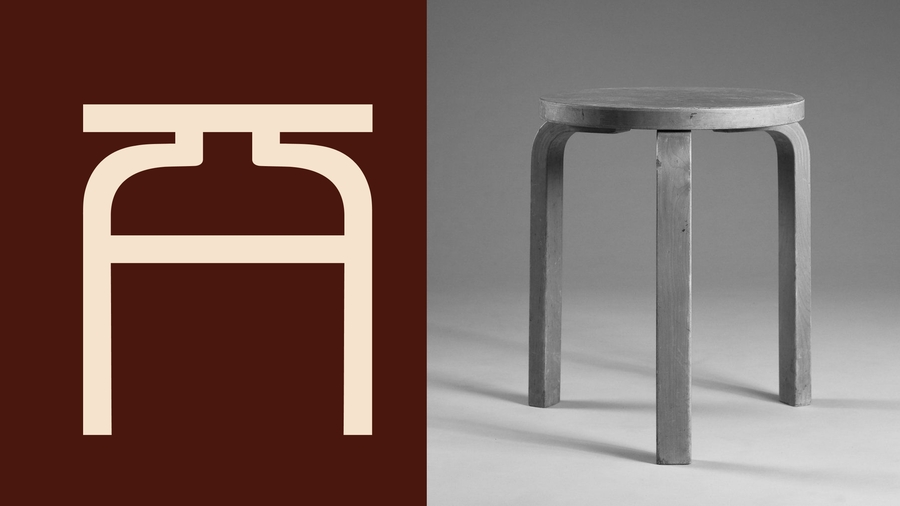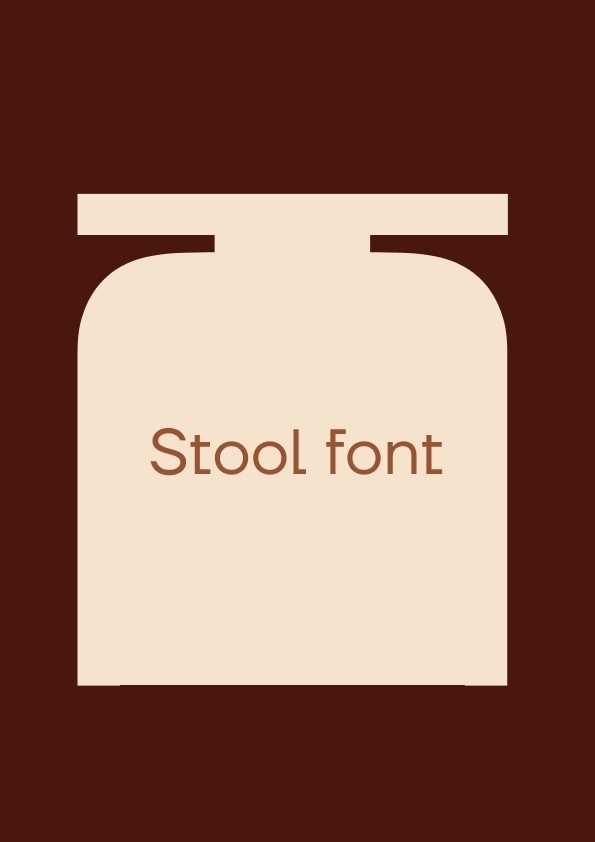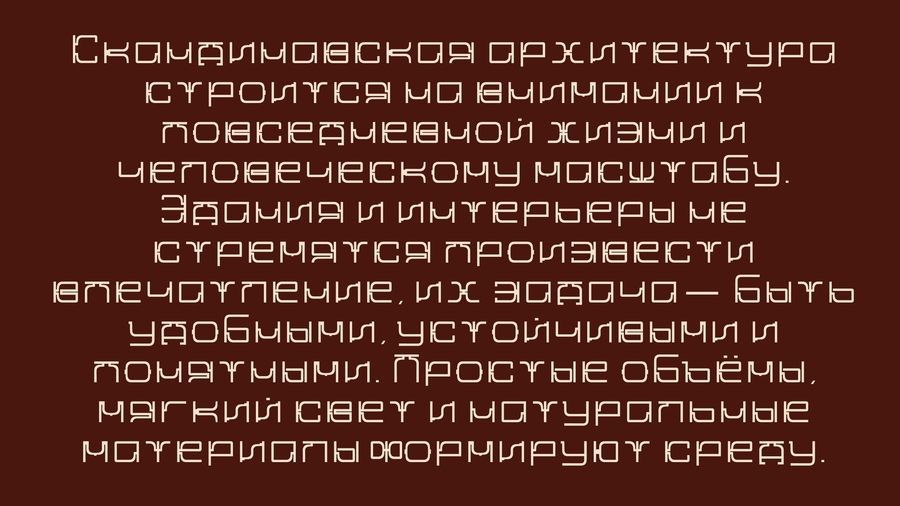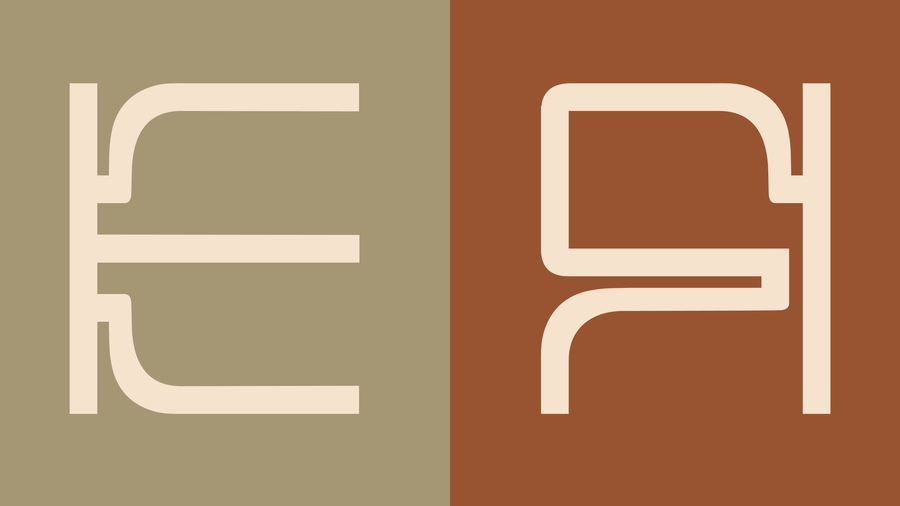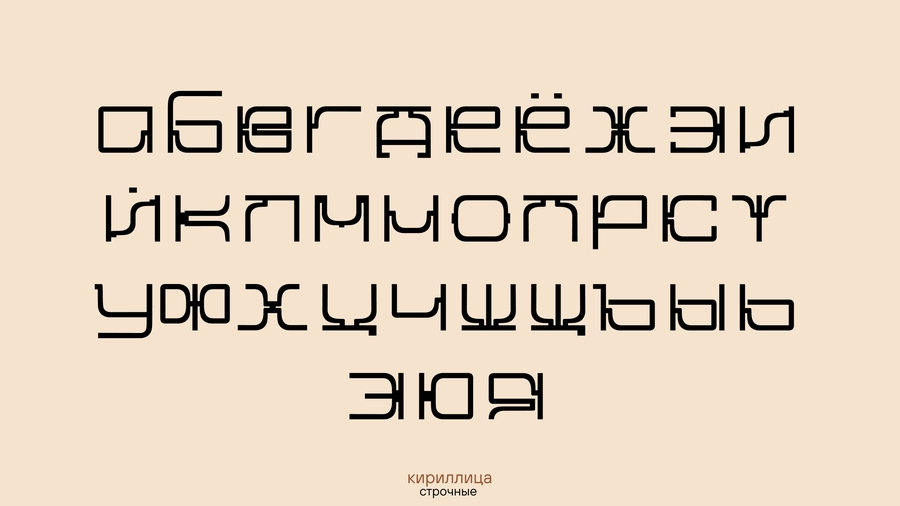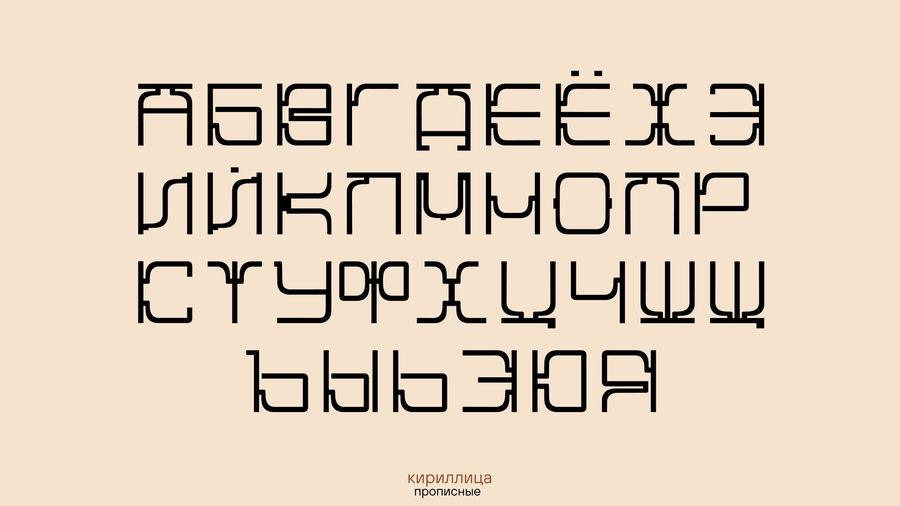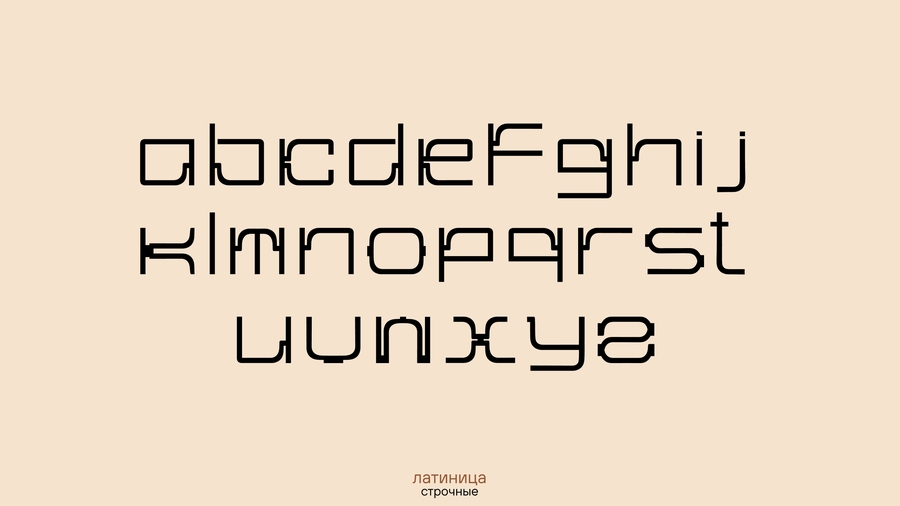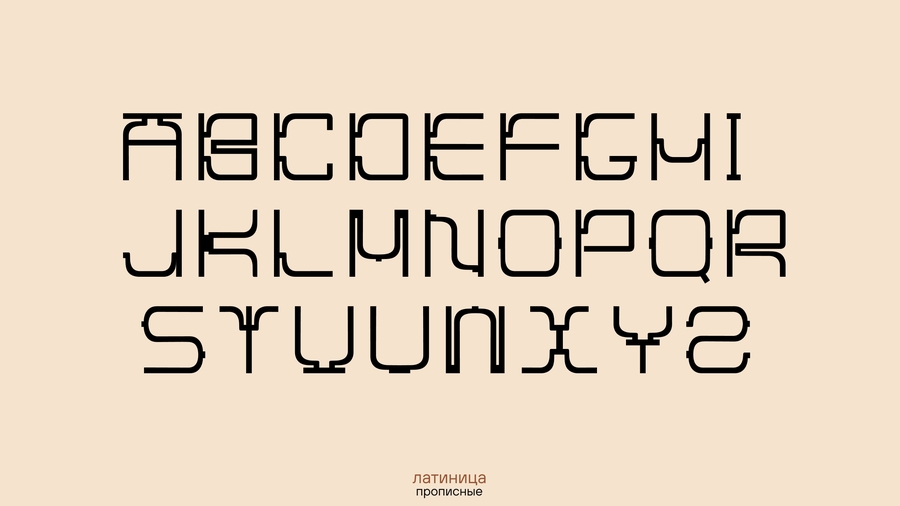
Stool font — акцидентный шрифт, вдохновлённый скандинавской архитектурой и мебельным дизайном.
Stool — архитектурно-интерьерное бюро, работающее на пересечении пространства, предмета и человеческого тела
Stool Font